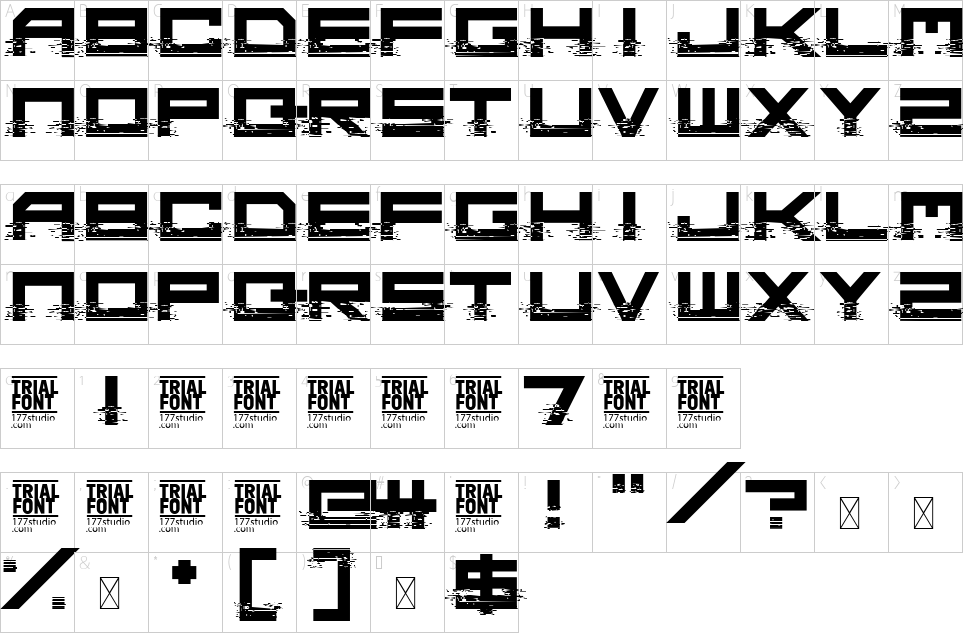
A Digital Glitch é uma fonte digital que traz para você uma experiência única, com traços irregulares que remetem a glitches digitais. Seu designer incógnito inspirou-se na interconexão entre arte e tecnologia para criar esta fonte, ideal para quem busca dar um toque único à sua página web ou material gráfico. Com seu formato multiplataforma, Digital Glitch é fácil de integrar em qualquer projeto, seja ele para Windows ou Mac. Esta fonte foi baixada 3.431 vezes, o que mostra a sua popularidade e capacidade de trazer vida aos projetos digitais. Se você busca algo diferente para dar um toque de originalidade a seu design digital, Digital Glitch é uma excelente escolha.